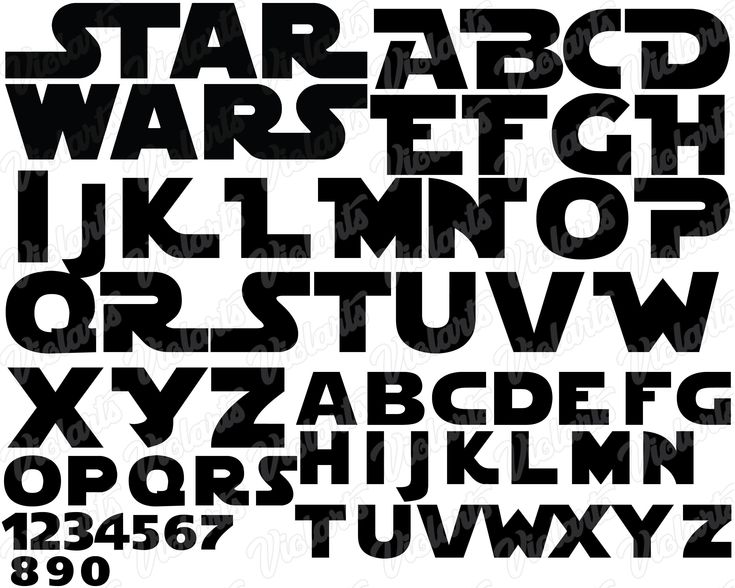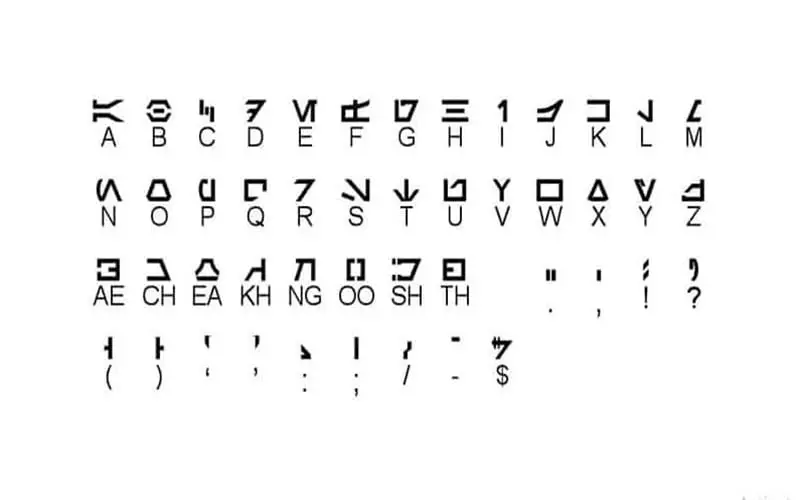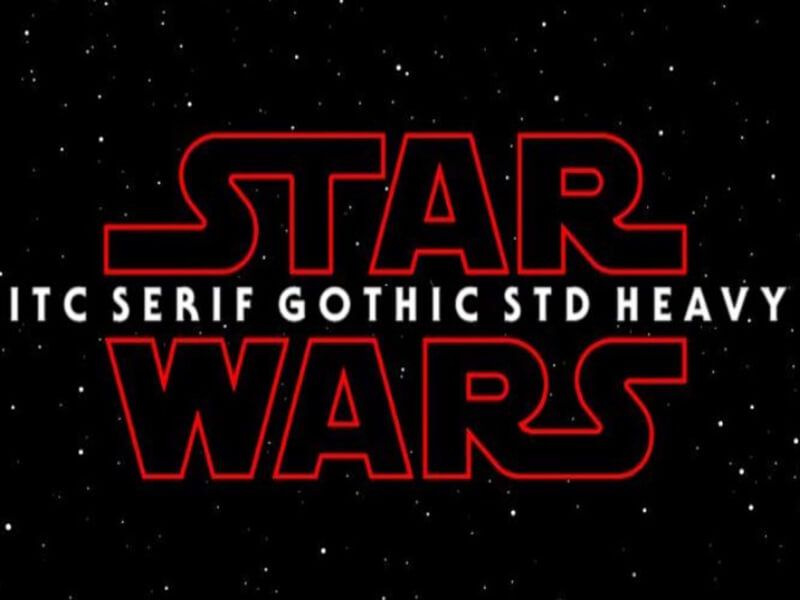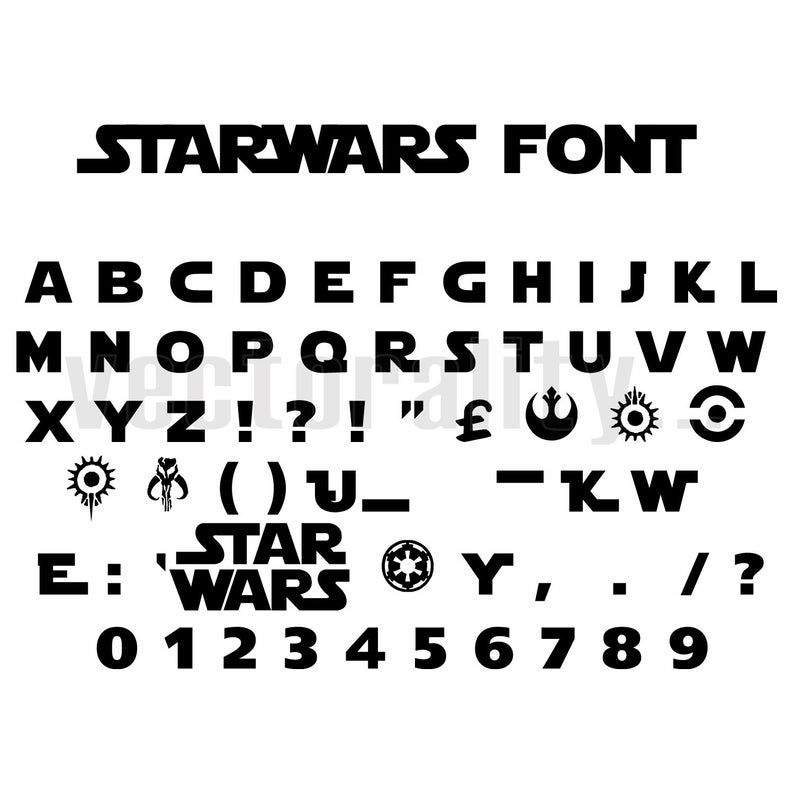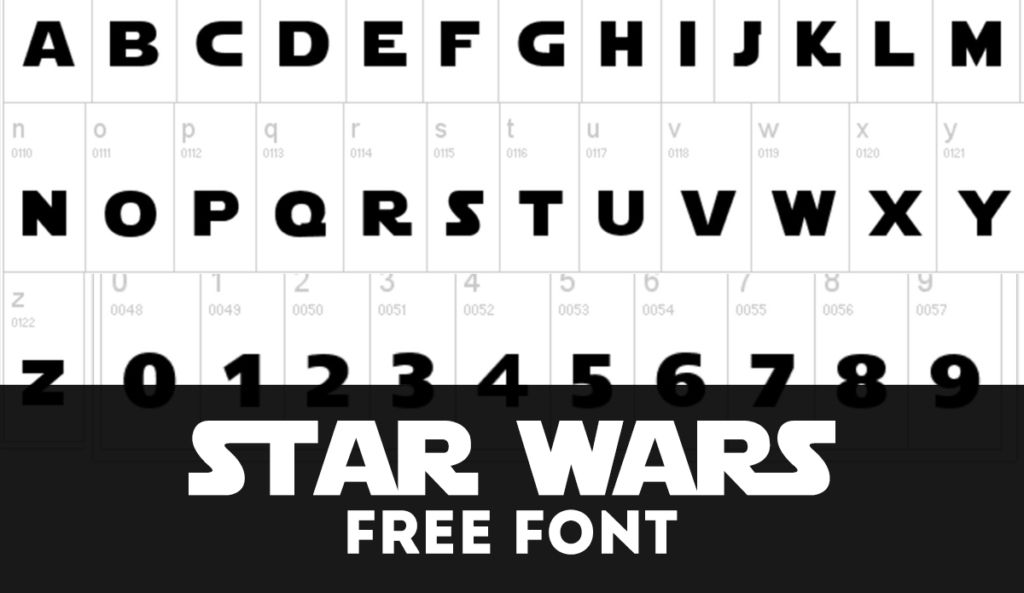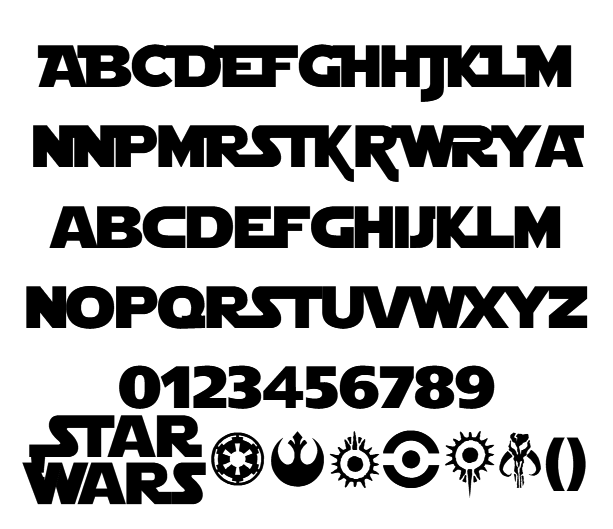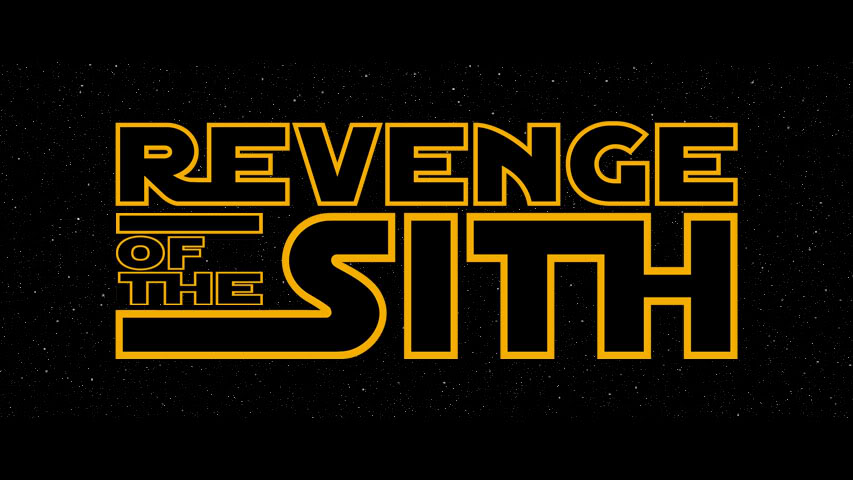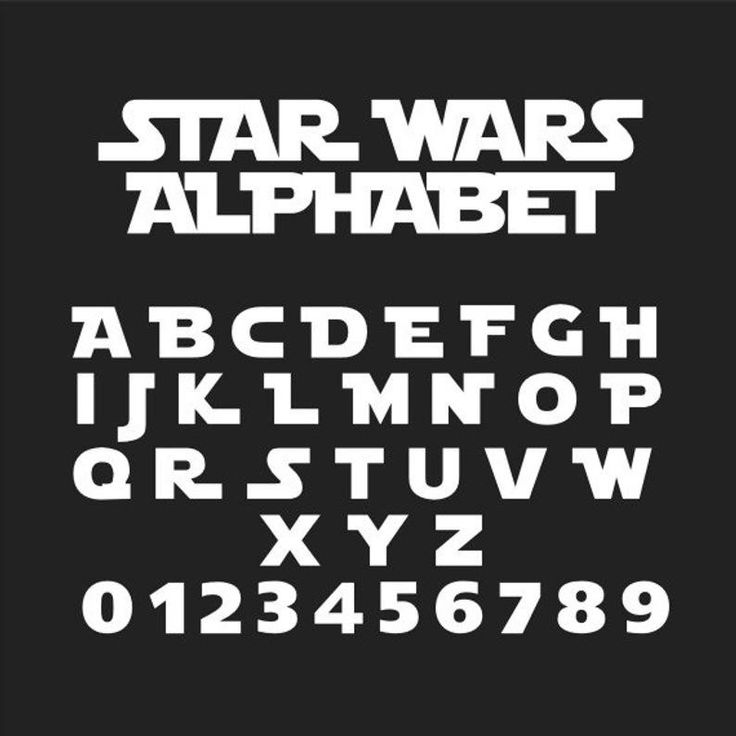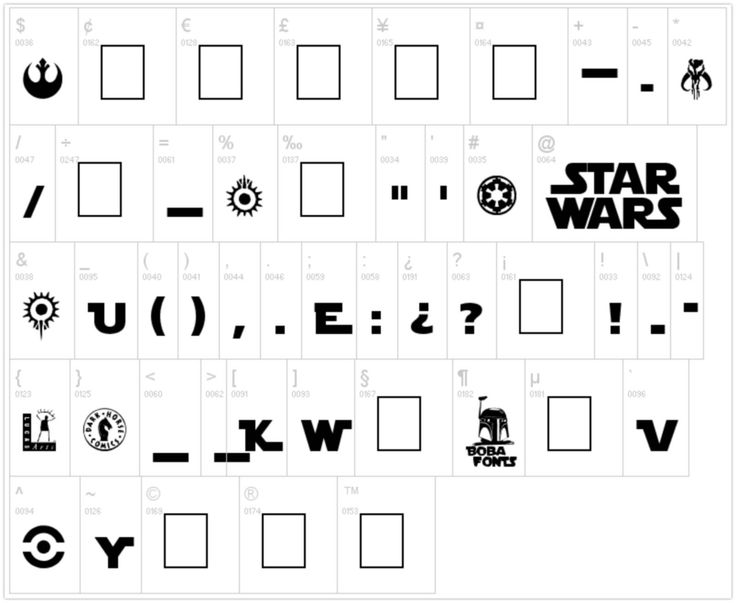
15 бесплатных шрифтов из далекой галактики
- Star Jedi
- Star Jedi Outline
- Sf Distant Galaxy
- Jedi
- Shadow of Xizor
- Death Star
- Anakinmono
- Starwars
- Redfive
- Mandalorian
- Star Jedi Logo
- Star Jedi Special Edition
- Aurek-Besh
- Rebellion
- Sigma Five
Скорее всего, вы читаете этот пост, потому что вы дизайнер, который ищет бесплатные футуристические или необычные шрифты, возможно, в стиле «Звездных войн». Оставшись здесь, вы находитесь в правильном месте. Мы собрали 15 великолепных шрифтов в стиле «Звездных войн». Все они бесплатные для использования. Если вам понравился шрифт, щелкните по его названию, и вы попадете на страницу скачивания.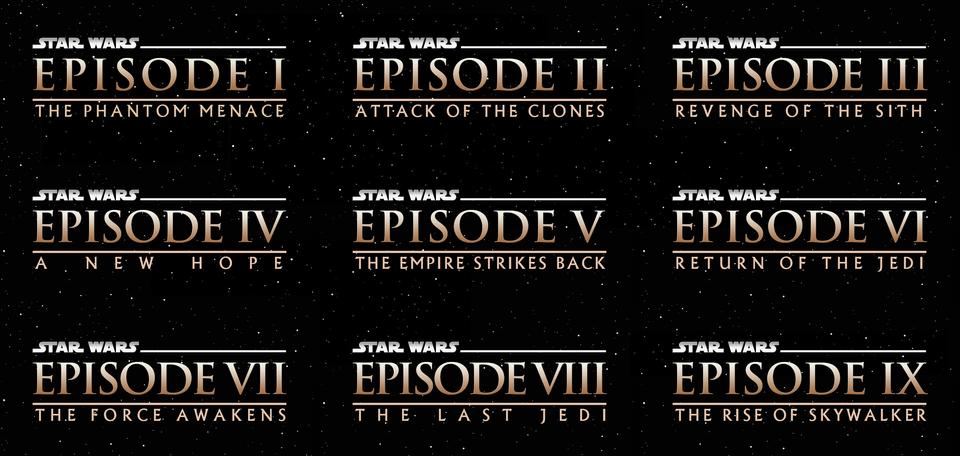
Более того, мы решили написатьсамые известные цитаты на языке оригинала франшизы и поместить их в сцены из разных эпизодов «Звездных войн». Так что впередза бесплатными шрифтами на фонекадров из любимого фильма.
Бесплатный шрифт Star Jedi
Эти шрифты логотипа Star Wars основаны на официальном шрифте логотипа Star Wars.Star Jedi — это титульный (только заглавные буквы) шрифт с множеством вариаций и связей.
Star Jedi Outline
Star Jedi Outline — это титульный (только заглавные буквы) шрифт с множеством вариаций и связей.Обратитесь к главному Звездному Джедаю за подробностями.SJ Outline также полностью совместим с серией логотипов: он может быть обрамлен линиями логотипа и использоваться с различными элементами логотипа.
Sf Distant Galaxy
Вдохновленная великим приключением в другой галактике, SF Distant Galaxy содержит строчные и заглавные буквы, цифры, знаки пунктуации и ударные символы.
Полный пакет шрифтов включает следующие десять шрифтов
Футуристический шрифт Jedi
Этот шрифт основан на droid-версии шрифта Aurebesh, используемого в Star Wars. Если у вас возникнут проблемы с апострофом и кавычками в Word, снимите флажок «прямые кавычки с умными кавычками» в настройках «Автозамены» Word.
Бесплатный шрифт Shadow of Xizor
Основанный на надписи для логотипа видеоигры, романа и комикса «Shadows of the Empire» «Звездные войны». Shadow of Xizor представляет собой шрифт с узким засечкой, который воспроизводит оригинальный шрифт логотипа Shadows of the Empire.
Шрифт Death Star
В далекой галактике далеко, у далеких поклонников этого эпического сериала были ограниченные возможности при поиске правильного шрифта для использования в своих проекты.Терпение, вы должны иметь молодого джедая и поблагодарить меня позже.Enter Death Star: гротескный шрифт с изображением всех заглавных букв, который напоминает классический стиль 80-х.